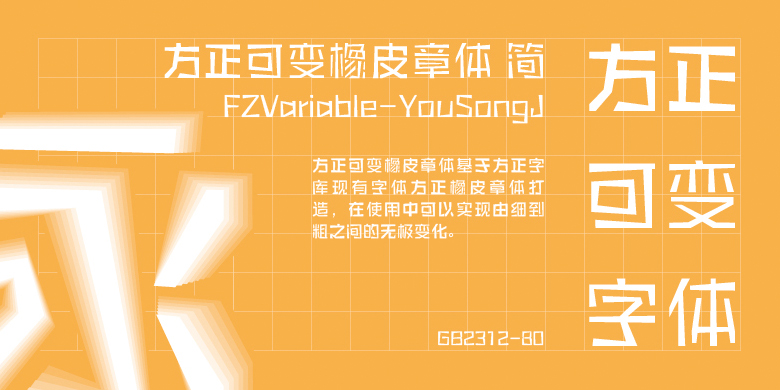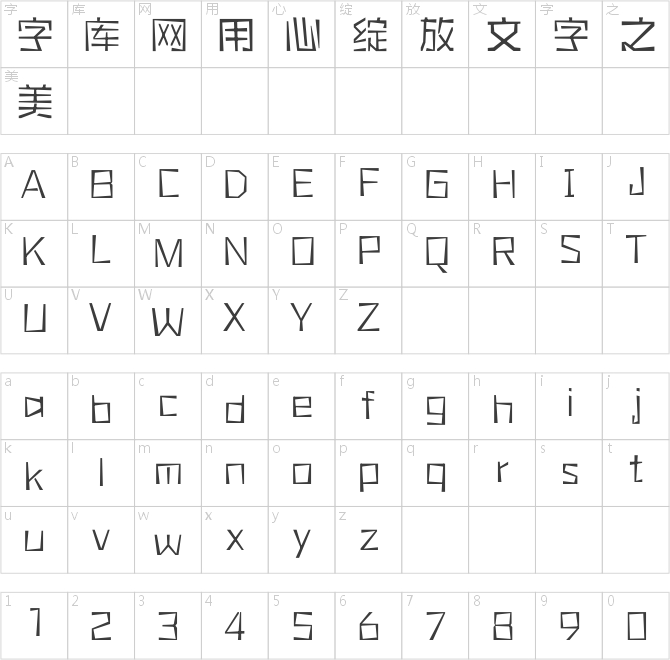
字體名稱: 方正可變橡皮章
方正可變橡皮章體 簡
方正可變橡皮章體支持文字粗細無級調節,設計師通過調整字重軸(Weight)的變化,可以實現字形的平滑連續的細微調整,滿足不同版式的設計需求。 中國漢字給人的感觀印象是“方塊字”,即在一塊面積大小相等的空間內,刻畫出一個個獨立的漢字。比如古代的“活字”雕刻,近代的機械打字機“字盤”。單字之間看似毫無關聯,可組合在一起,就能體現出正負空間的強烈對比,方陣嚴整。 該字體筆畫的安排,沿襲著橡皮章雕刻特有的平直、硬朗,打破傳統的“橫平豎直”,增加字體的動感,有古老石碑的拓印之風,不失時尚潮流的文藝之美,無論是橫排或豎排,行列之間整齊有序,給人予方塊拼接,搭積木之美感,可廣泛用于報紙、雜志、包裝、廣告等印刷品的標題、正文。